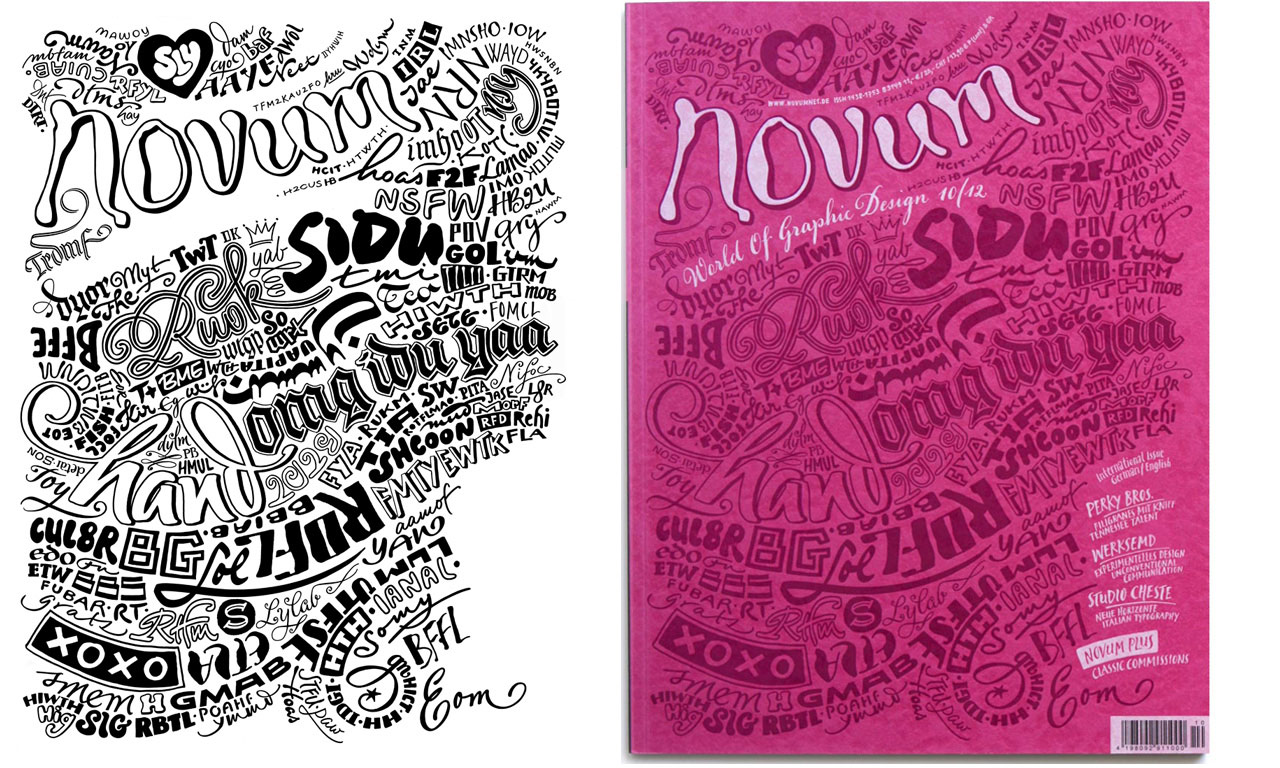
Novum_Cover
Entworfen und geschrieben für:
Novum
Druck:
Bölling Prägedruck, Bad Soden
Papier:
Gmund Stone von Römerturm
Für die Covergestaltung der Novum-Oktoberausgabe 2012 habe ich Akronyme des Chats, eher als schnelle und flüchtige Zeichen bekannt, in einer Kombination aus Kalligrafie und Handlettering umgesetzt. Gedruckt wurde die Lettering-Collage im klassischen Buchdruck auf Gmund Stone von Römerturm. Innerhalb der Auflage sind drei unterschiedliche Farben zum Einsatz gekommen.